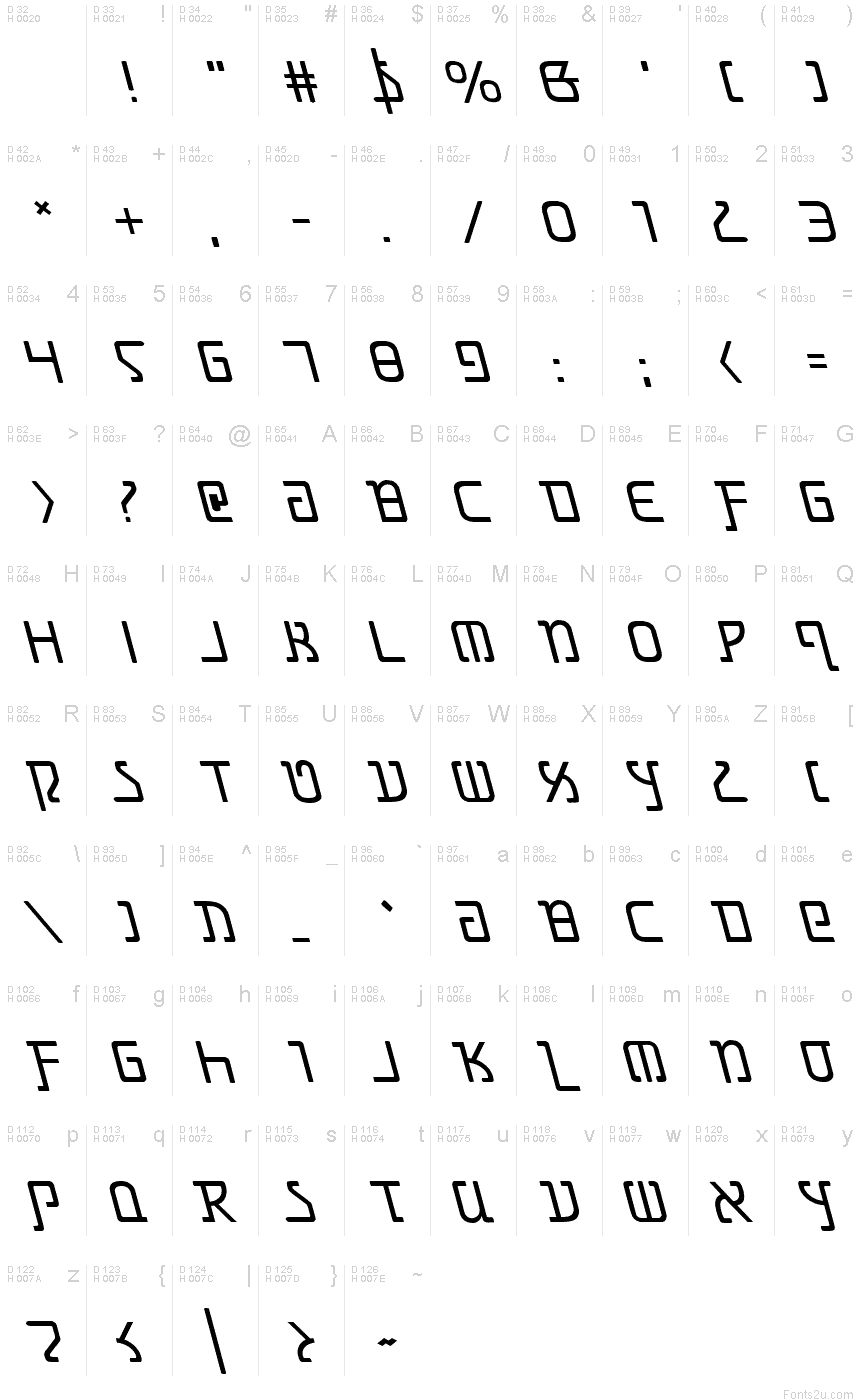
Grimlord Leftalic autorstwa Iconian Fonts to darmowy, futurystyczny krój akcydensowy zbudowany z wysokich kapitelików z szerokimi skośnymi pociągiami, kwadratowymi łukami, ściętymi narożnikami i wyraźnym pochyleniem wstecznym. Jego kanciasta konstrukcja przywołuje na myśl liternictwo tytułów science-fiction oraz wczesną grafikę z automatów do gier.
Jako teatralny tytuł lub elektroniczna insygnia może zmienić okładki gier, plakaty muzyczne, grafiki imprezowe i gadżety w część fikcyjnego interfejsu zamiast zwykłego oznakowania. Surowa geometria trafia najbardziej bezpośrednio do fanów science-fiction, cyberpunku i retro-gamingu, zwłaszcza w brandingu rozrywkowym ukształtowanym wokół maszyn i fikcyjnej technologii.
Grimlord Leftalic